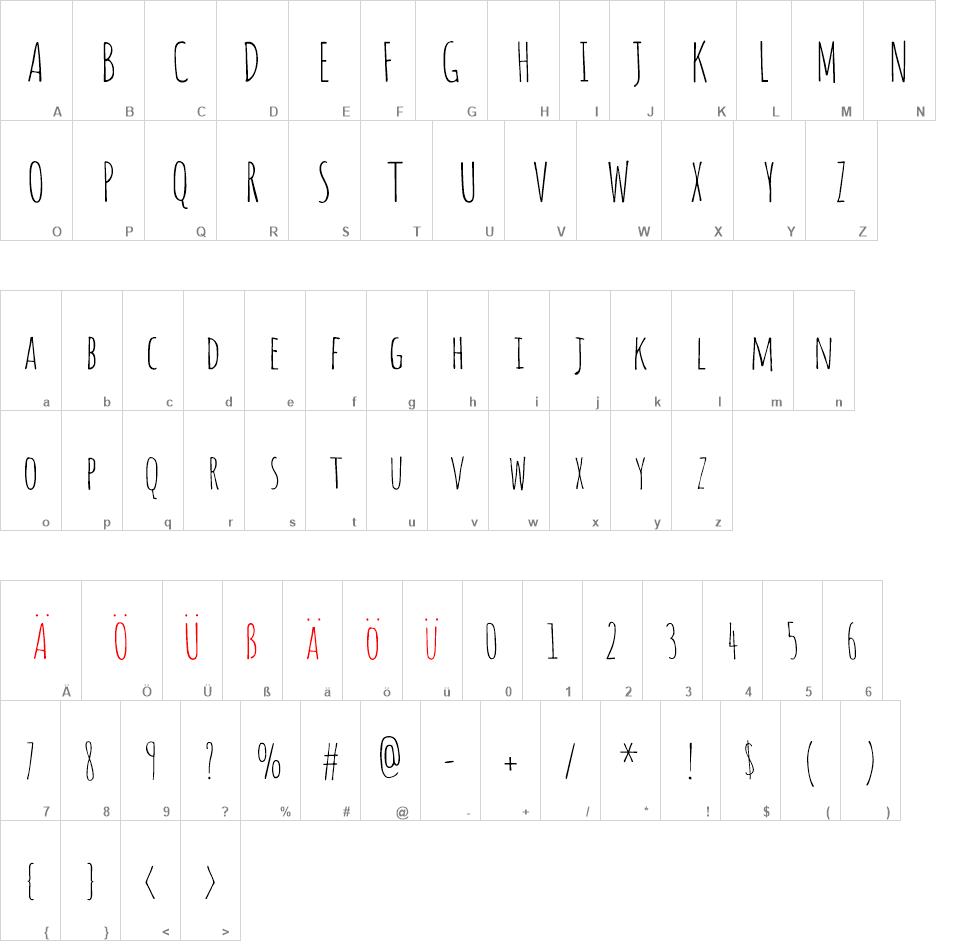
Amatica SC
Amatica SC font
Eine lustige Schriftart für lustige Leute! Amatica SC begann als Durchbruch der beliebten Amatic SC-Familie von Vernon Adams. Ben Nathan, ein israelischer Designer, fügte eine hebräische Komponente hinzu und korrigierte das Latein in vielerlei Hinsicht, vor allem, um den Bereich der Buchstaben so zu erweitern, dass er zu den meisten Hebräern passt.